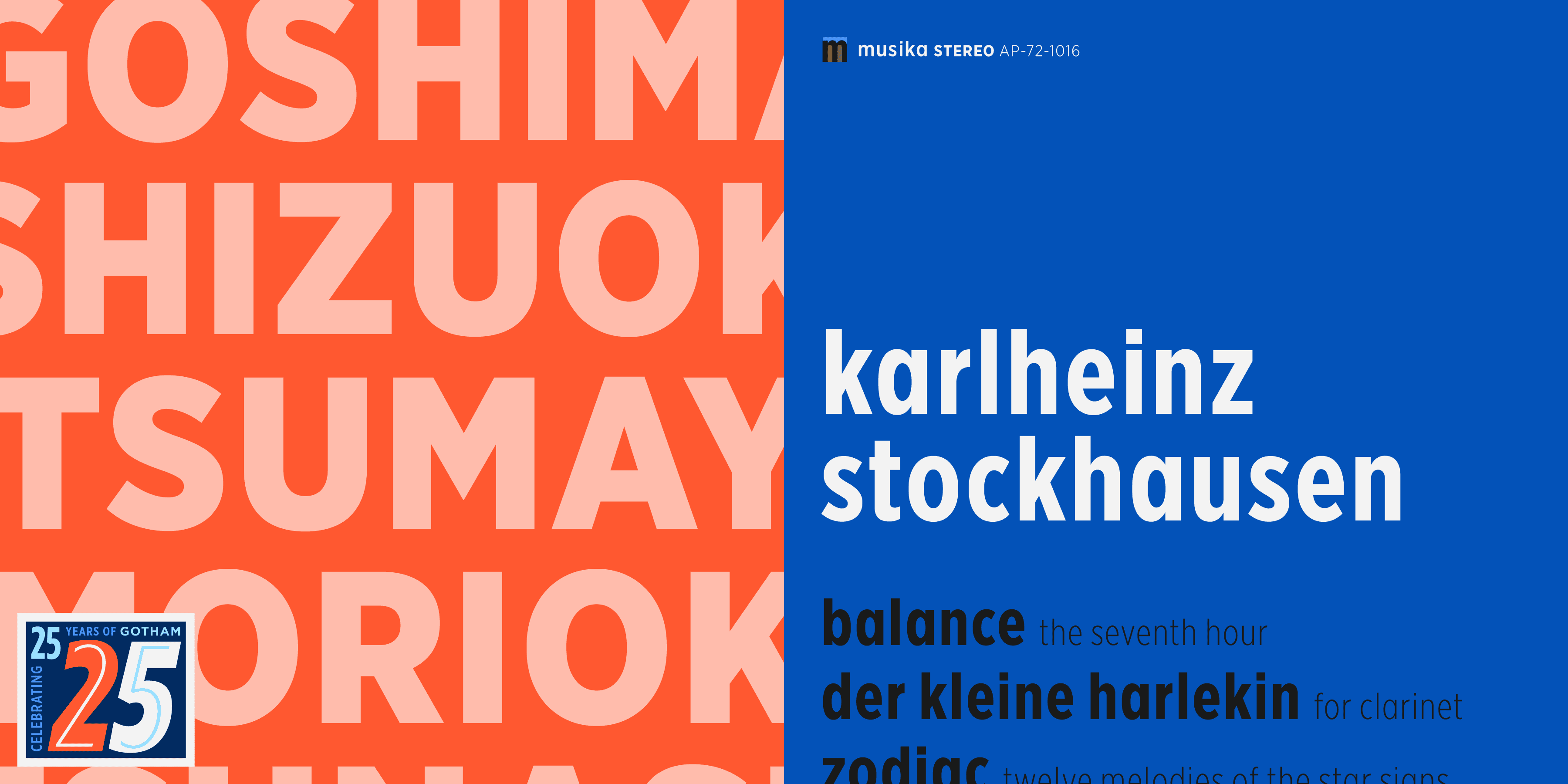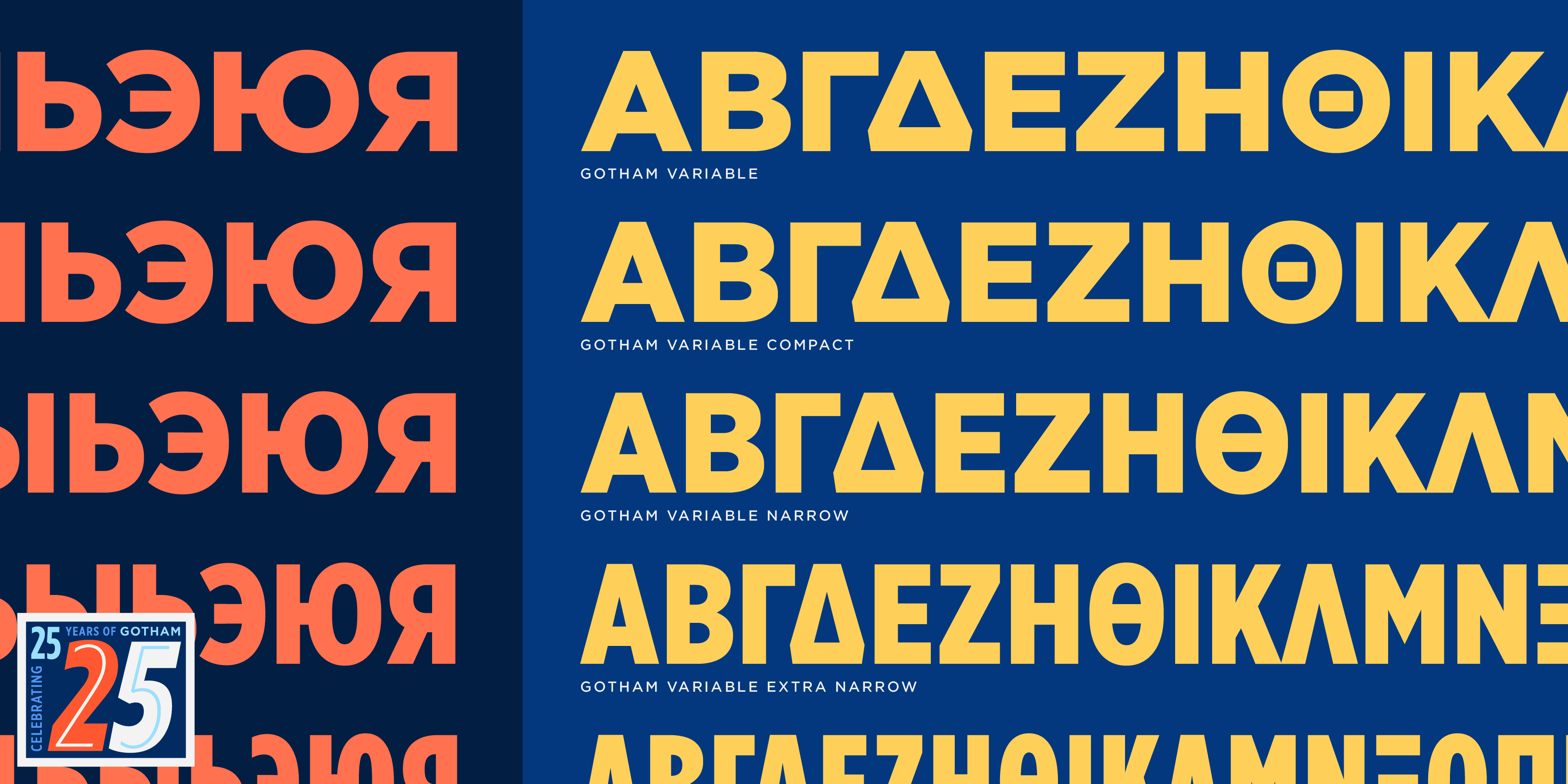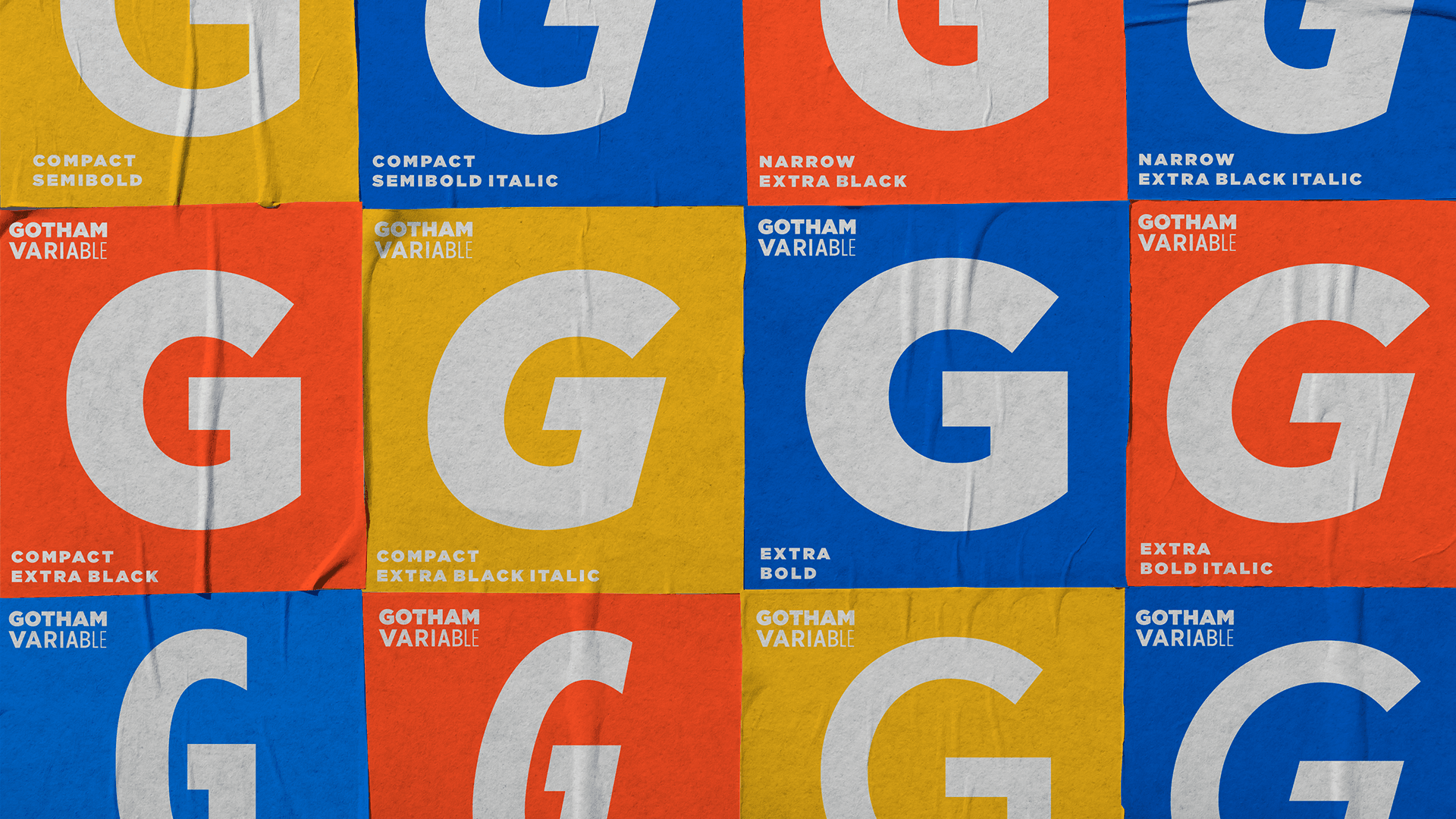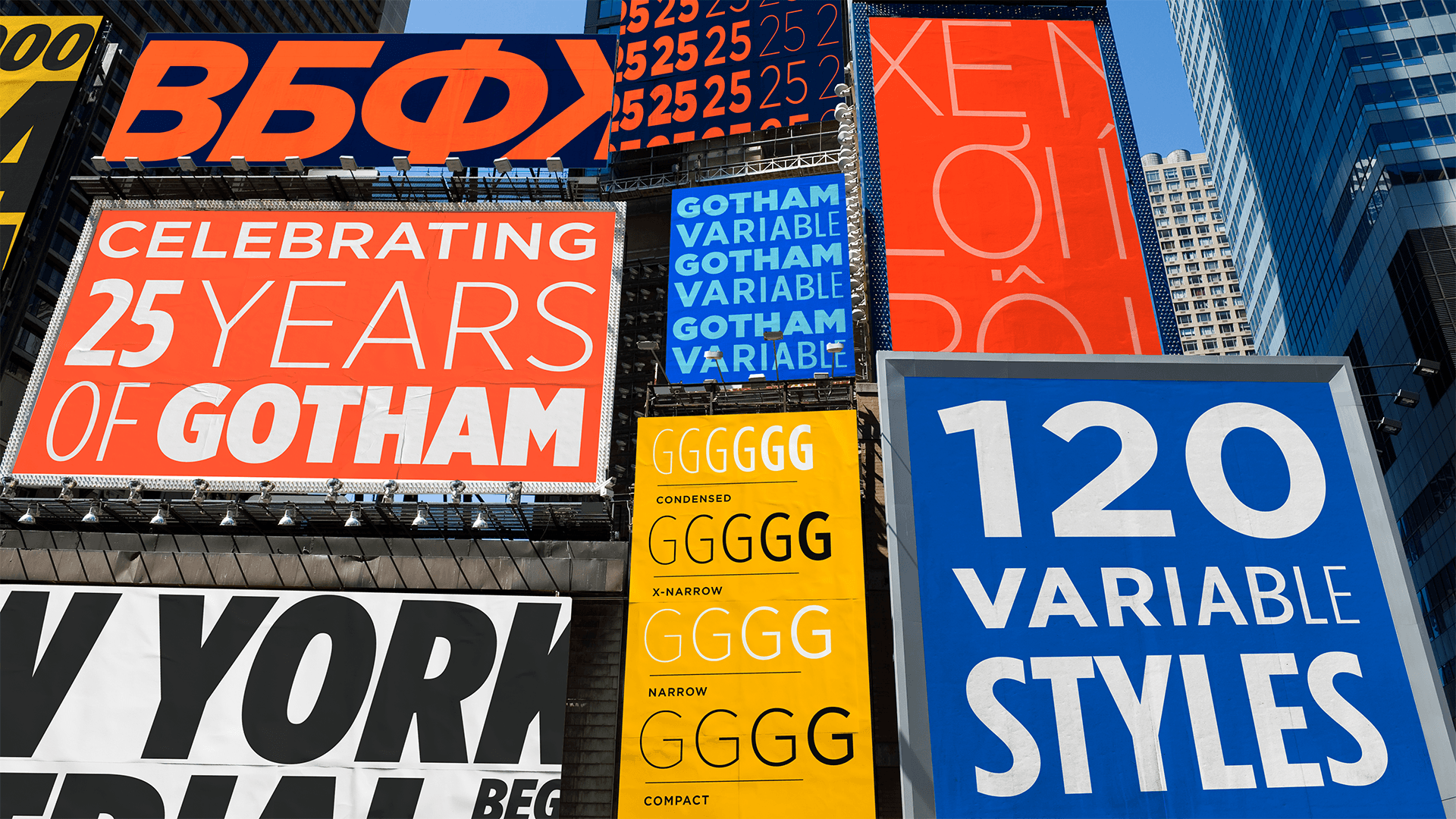
모노타입, 고담 25주년 기념 ‘고담 배리어블’ 출시…브랜드 디자인을 위한 유연한 서체 시스템으로 확장
서체 및 폰트 기술 분야의 글로벌 리더 모노타입(Monotype)은 고담(Gotham®) 서체를 가변 서체로 확장한 고담 배리어블(Gotham® Variable)을 출시했다고 밝혔다. 고담 배리어블은 디자이너가 굵기와 폭을 자유롭게 조정할 수 있는 가변 서체로, 브랜드, 디지털 제품, 다양한 고객 접점에서 보다 정교한 타이포그래피 표현을 가능하게 한다.
고담은 지난 25년 동안 전 세계에서 가장 널리 알려진 서체 중 하나로 자리 잡았다. 브랜드 아이덴티티와 광고, 정치 캠페인, 엔터테인먼트 등 다양한 분야에서 사용되며 현대 커뮤니케이션의 시각적 이미지를 만들어 왔다. 조나단 호플러(Jonathan Hoefler)와 토비아스 프레어-존스(Tobias Frere-Jones)가 디자인하고 호플러 앤 코(Hoefler & Co.)가 발표한 고담은 2001년 1월 GQ 표지를 통해 처음 대중에게 공개됐다.
고담 배리어블은 고담 특유의 명료하고 자신감 있는 인상을 유지하면서, 오늘날의 디자인 환경에 필요한 유연성을 더했다. 디자이너는 서체를 바꾸지 않고도 굵기와 폭을 조정해 차분한 분위기부터 강한 존재감이 필요한 표현까지 폭넓게 만들 수 있다. 또한 파일 구조를 간소화해 성능을 높이고 로딩 시간을 줄였으며, 여러 플랫폼에서 보다 쉽게 적용할 수 있도록 했다.
사라 소스콜네(Sara Soskolne) 모노타입 총괄 크리에이티브 디렉터이자 고담 배리어블 리드 디자이너는 “고담은 지난 25년 동안 정치 캠페인과 옥외 광고, 세계적인 브랜드 아이덴티티에 이르기까지 다양한 분야에서 높은 신뢰를 쌓아왔다”며 “고담 배리어블을 만들며 가장 중요하게 생각한 것은 고담의 유산을 지키면서도, 이 서체가 앞으로 어떻게 확장될 수 있는지를 보여주는 일이었다. 기존에 없던 새로운 스타일들이 고담 안에 자연스럽게 녹아들도록 만드는 과정이 가장 어렵고도 중요한 작업이었다”고 말했다.
이번 버전에서는 언어 지원도 확대됐다. 특히 베트남어 지원을 추가해 복합적인 발음 구별 기호와 성조 표기를 보다 정교하게 표현할 수 있다. 이를 통해 브랜드는 더 많은 언어권에서 일관된 브랜드 이미지를 유지하면서도, 각 지역의 언어적 특성을 반영한 커뮤니케이션을 전개할 수 있다.
조던 벨(Jordan Bell) 모노타입 시니어 서체 디자이너는 “기존 서체 패밀리에 새로운 언어를 추가하는 일은 단순히 글자를 더하는 작업이 아니다”며 “새로운 글자 형태가 고담의 전체적인 인상과 조화를 이루도록 비례와 스타일을 세심하게 다듬는 과정이 필요했다. 특히 베트남어 표기에 중요한 후크(hook)와 혼(horn)에서도 고담 특유의 표현력을 유지하는 데 중점을 뒀다”고 설명했다.
모노타입은 고담 배리어블을 통해 가변 서체로서의 활용성을 높이는 동시에, 고담 패밀리의 표현 범위를 넓히는 54종의 새로운 스타일도 추가했다. 이를 통해 디자이너는 프로젝트의 목적과 매체에 따라 더욱 세밀한 타이포그래피 선택을 할 수 있다.
고담은 넷플릭스와 코카콜라를 비롯한 글로벌 브랜드, 미국 우정청(USPS)과 같은 기관, 새터데이 나이트 라이브(Saturday Night Live) 같은 문화 플랫폼의 브랜드 이미지를 구축하는 데 사용되어 왔다. 또한 버락 오바마 대통령 선거 캠페인의 시각적 이미지를 형성하는 데에도 기여했다.